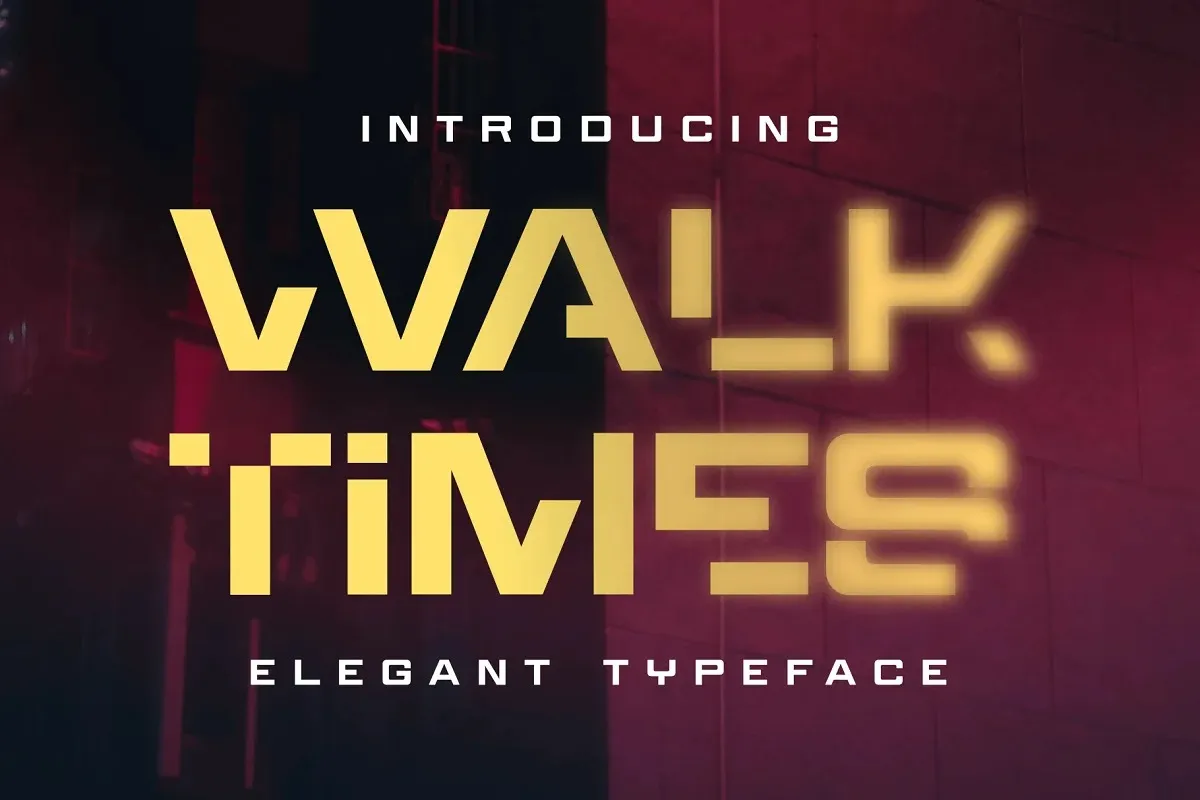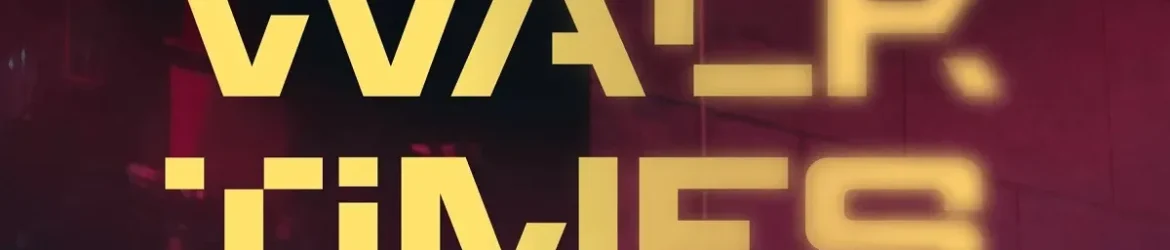
A Walktimes Font é uma escolha perfeita para quem busca expressar modernidade e inovação em seus projetos digitais e impressos. Esse tipo de display font traz uma visão futurista à sua identidade visual, com oito números únicos e alternativas galácticas, que se destaca e chama atenção. Ideal para criar logo’s inovadores, destacar mensagens nas redes sociais ou em anúncios digitais, projetos de marca, embalagens de produtos, gráficos e design cinematográfico, textos da mídia social e até mesmo materiais promocionais, a Walktimes é um recurso visual que se destaca. Com sua estrutura futurista e seu estilo único, a Walktimes torna-se uma escolha inteligente para designers e criativos em busca de criar designs modernos e impactantes.